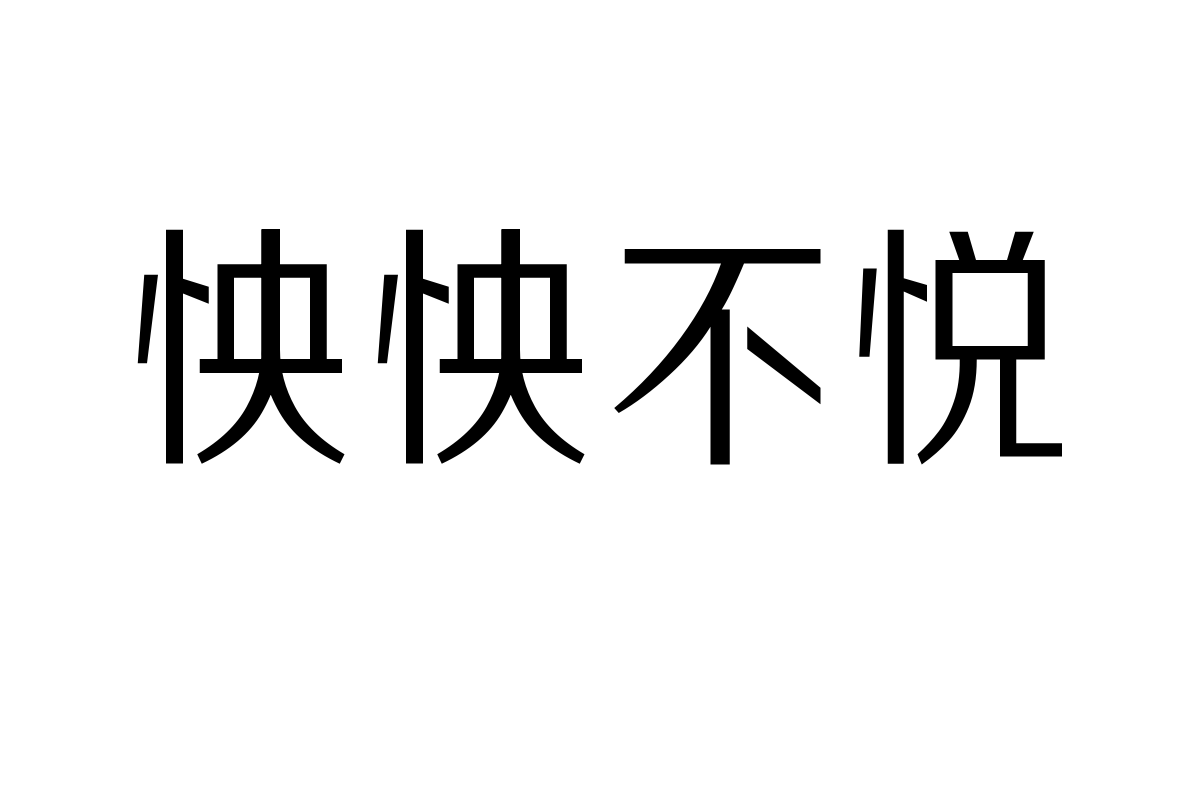
三极正雅黑字体是一款具有现代感和艺术感的中文字体。它采用了独特的字形设计和排版风格,使得文字看起来更加美观、大方。这款字体适用于各种需要展示文字内容的场合,如广告设计、网页设计、书籍封面等。
三极正雅黑字体的特点包括:
1. 字形独特:这款字体采用了独特的字形设计,使得文字看起来更加美观、大方。
2. 排版自由:三极正雅黑字体支持多种排版方式,可以根据设计需求进行灵活调整。
4. 可定制性高:三极正雅黑字体提供了丰富的字体样式和参数设置,可以满足不同设计师的需求。
总之,三极正雅黑字体是一款功能强大、适用范围广泛的中文字体,适用于各种需要展示文字内容的场合。